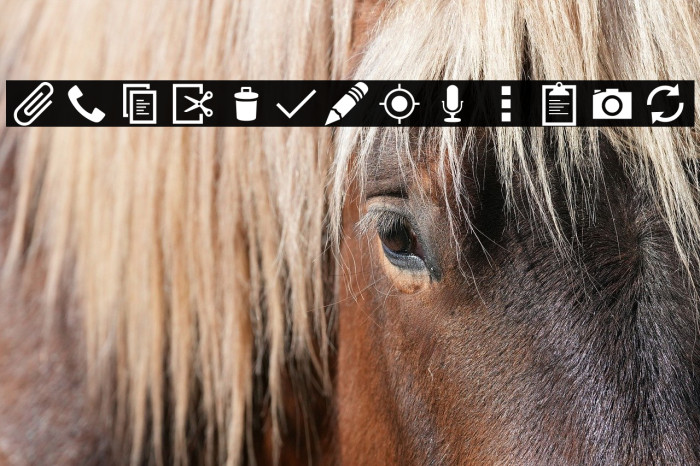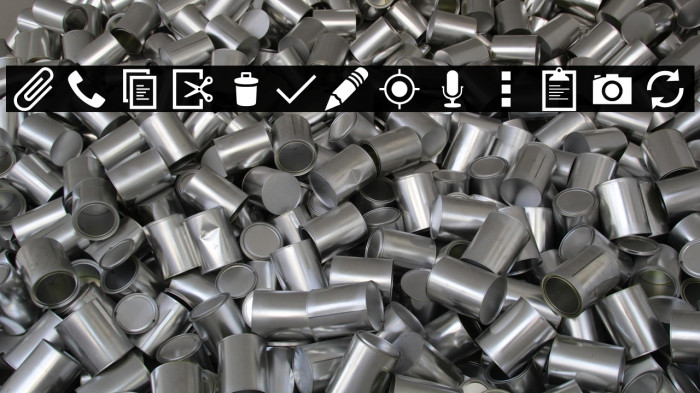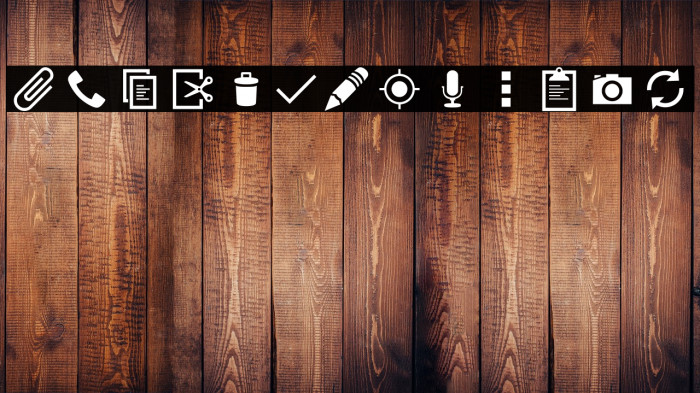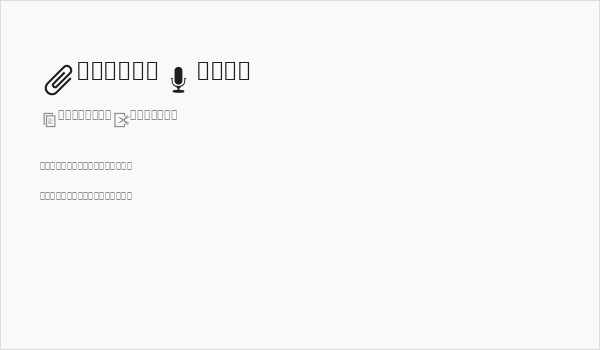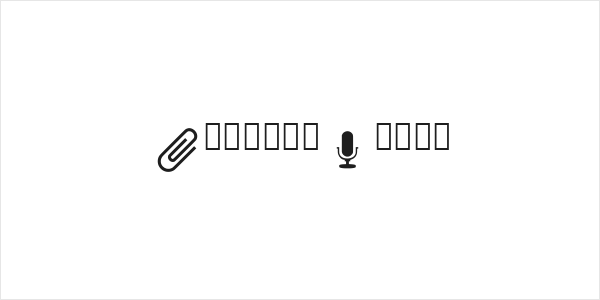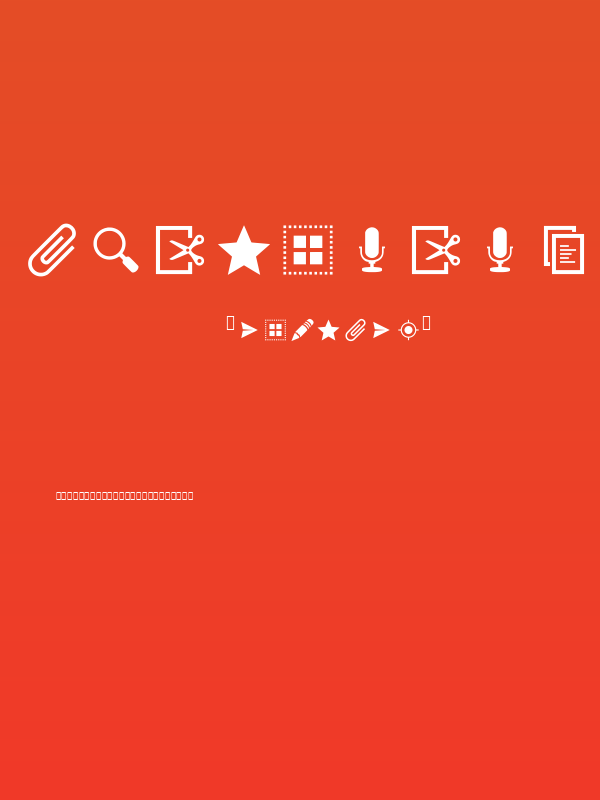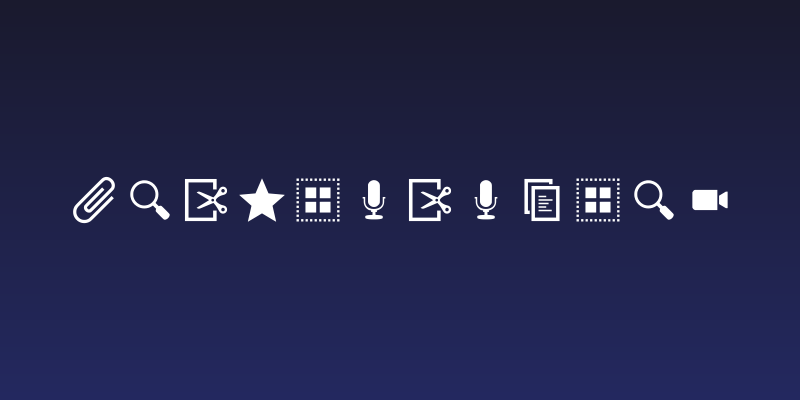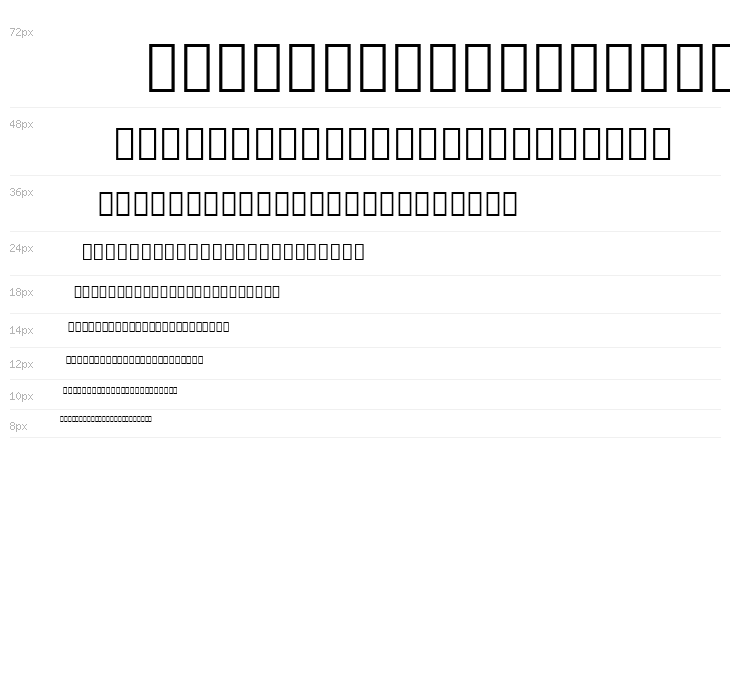
AndroidIcons Font
✎ Dingbats
| 整体风格 | Modern, Minimalist |
| 使用场景 | Icons for interfaces, buttons, and toolbars. |
| 推荐项目 | Mobile apps, web interfaces, dashboards, toolbars, software UI, quick action menus. |